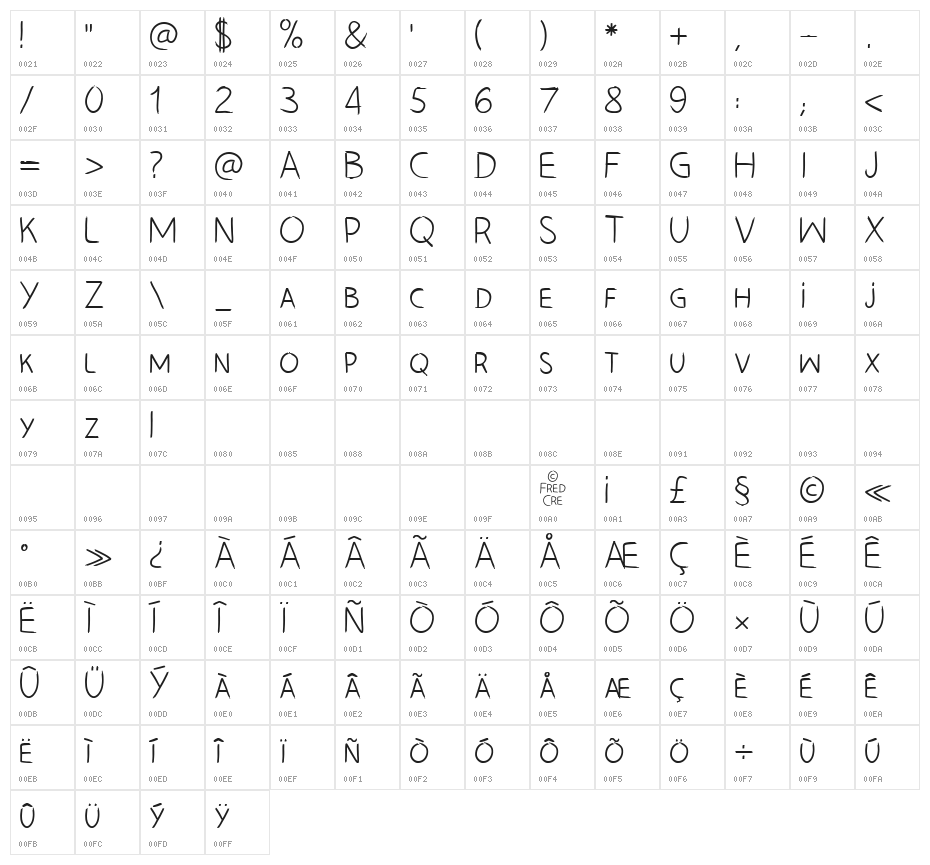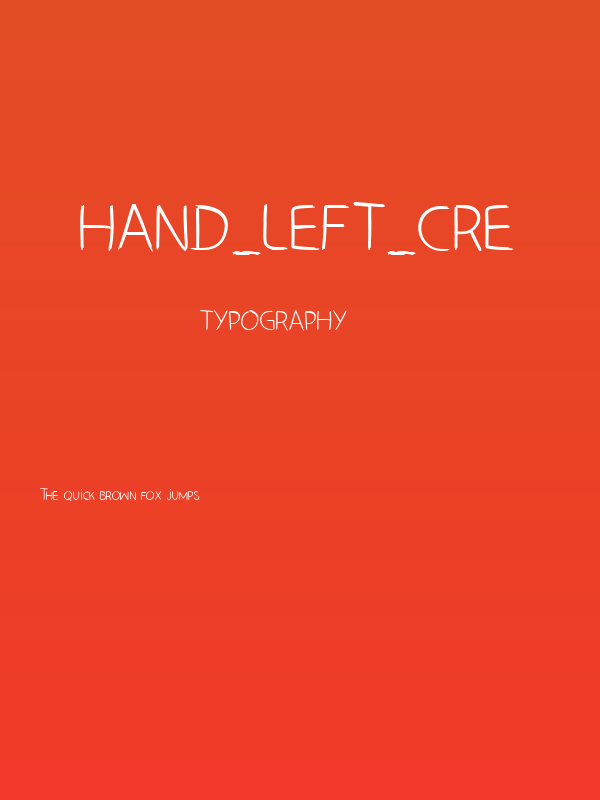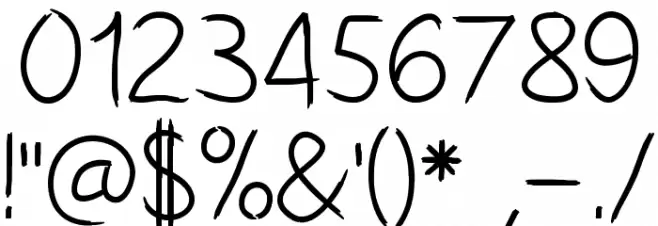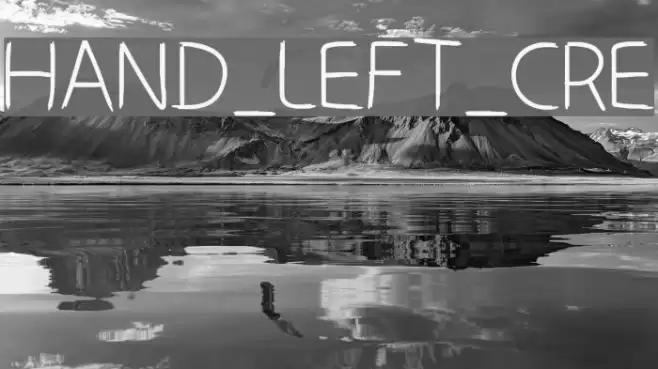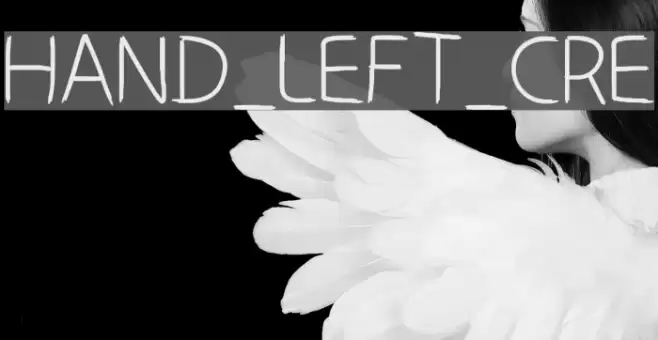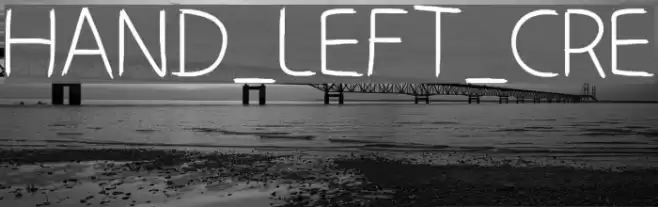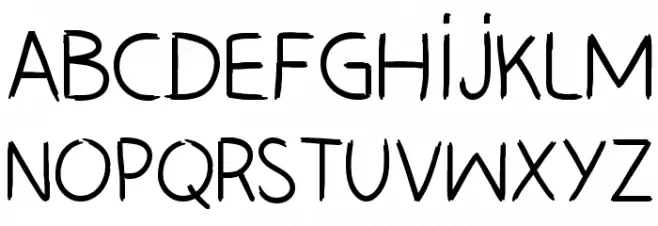
HAND_LEFT_CRE Font
| Stil general | Casual, Playful |
| Caz de utilizare | Headlines, Informal text, Personal projects |
| Proiecte propuse | Ideal for greeting cards, children's books, casual invitations, and personal branding. |